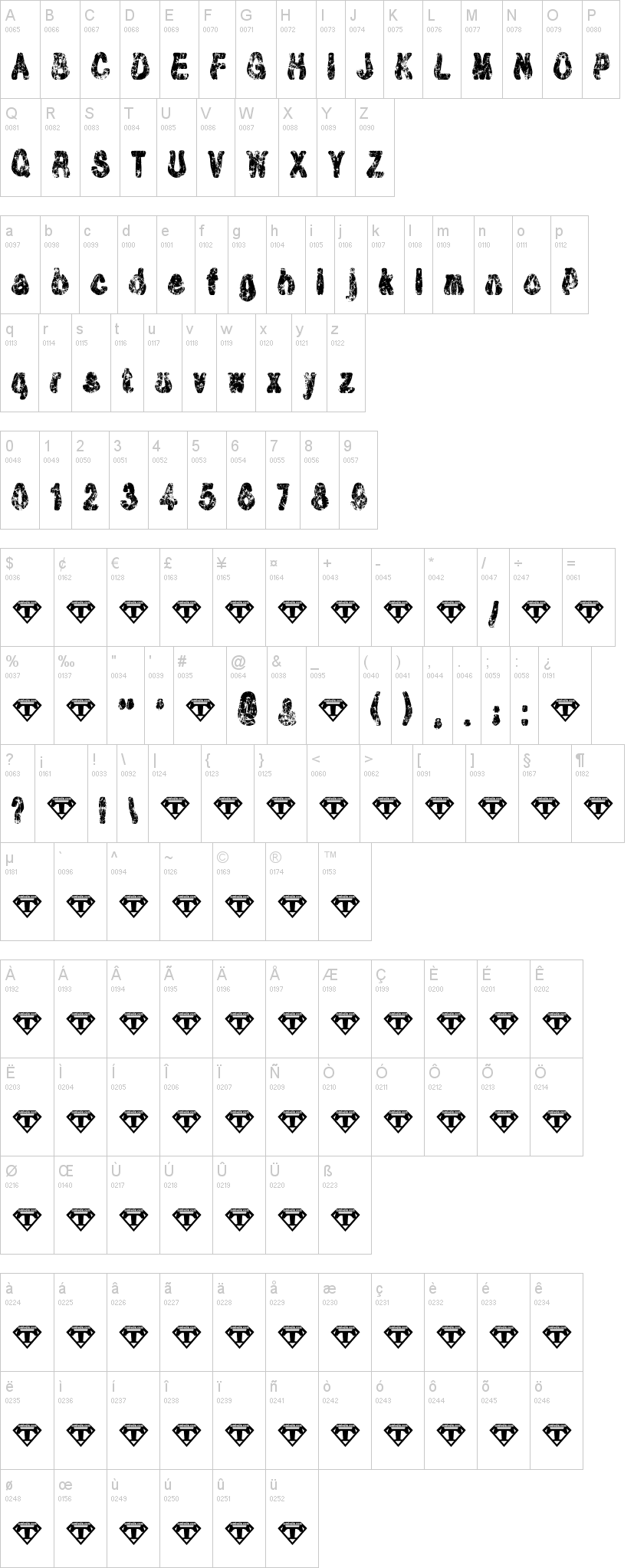
Tioem Black Distressed
Tiem Black Distressed 是一种漂亮的无衬线字体,具有独特的黑色破损效果。它基于Tiém Regular字体设计而成,适用于各种设计项目,如海报、标志、包装设计等等。它的设计风格简洁大方,字母间距适当,使得它易于阅读和识别。Tiem Black Distressed 字体可以用于各种场合,尤其是那些需要一种有独特风格的字体来突出重点的时候。
Tioem Black Distressed是一款非常不错的手写艺术字体,具有很好的视觉感,适合于文化类的宣传设计、商业类品牌的广告和产品包装设计以及个性化文字排版等较多场景。
Tioem Black Distressed字符映射图